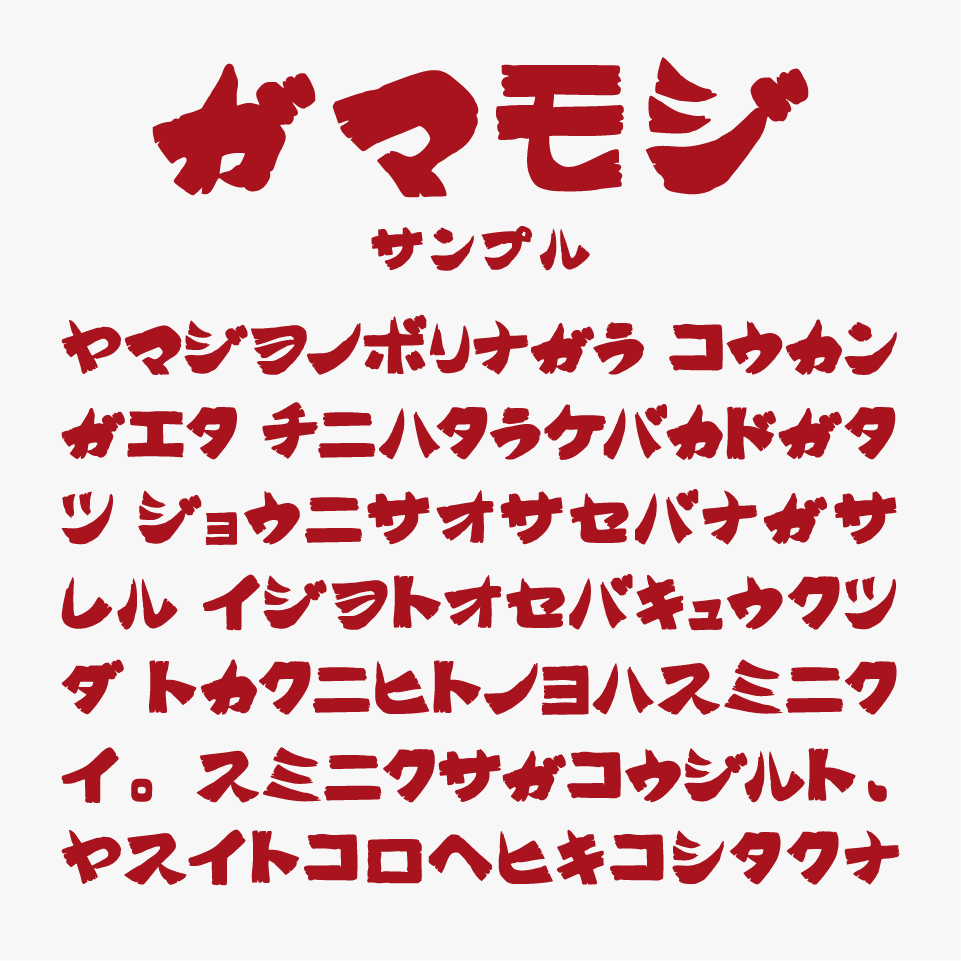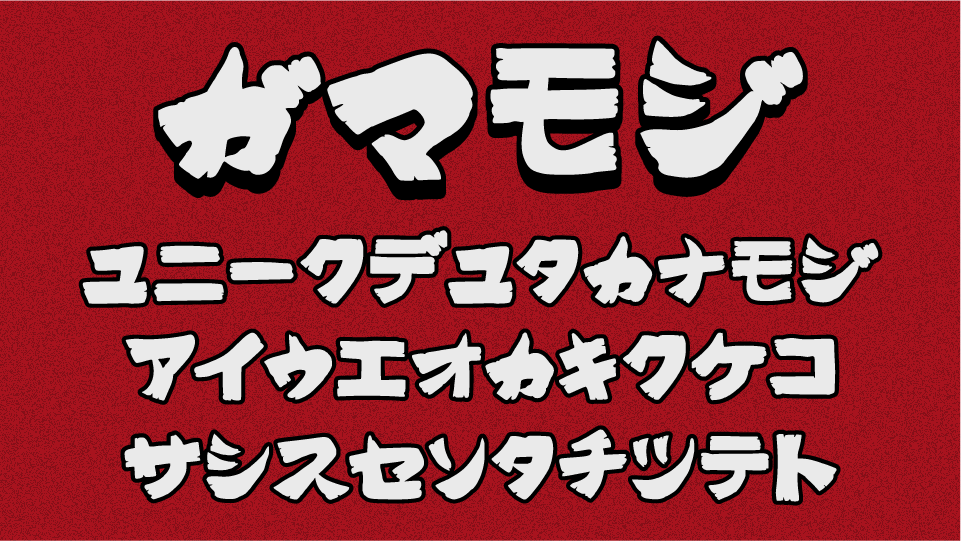
ガマ文字フォントは、茨城県・つくば市の筑波山にある「ガマランド」内の看板や案内板などに使用されている文字から作られてたフォントです。
1971年に建てられ、昭和のノスタルジックな哀愁が漂う遊園地「ガマランド」(現在は整備中とのこと。)
「ガマ文字発見プロジェクト」と称して、参加者に園内の文字を探索してもらい、レタリングをして、フォント化するといったワークショップ形式で、作られたユニークな取り組みから生まれたフォントです。(詳しい内容はこちらから)
太く荒々しいラインと、跳ねや払いの力強さが、強烈な印象を感じるデザインとなっているフォントです。
収録文字は、カタカナが収録されています。